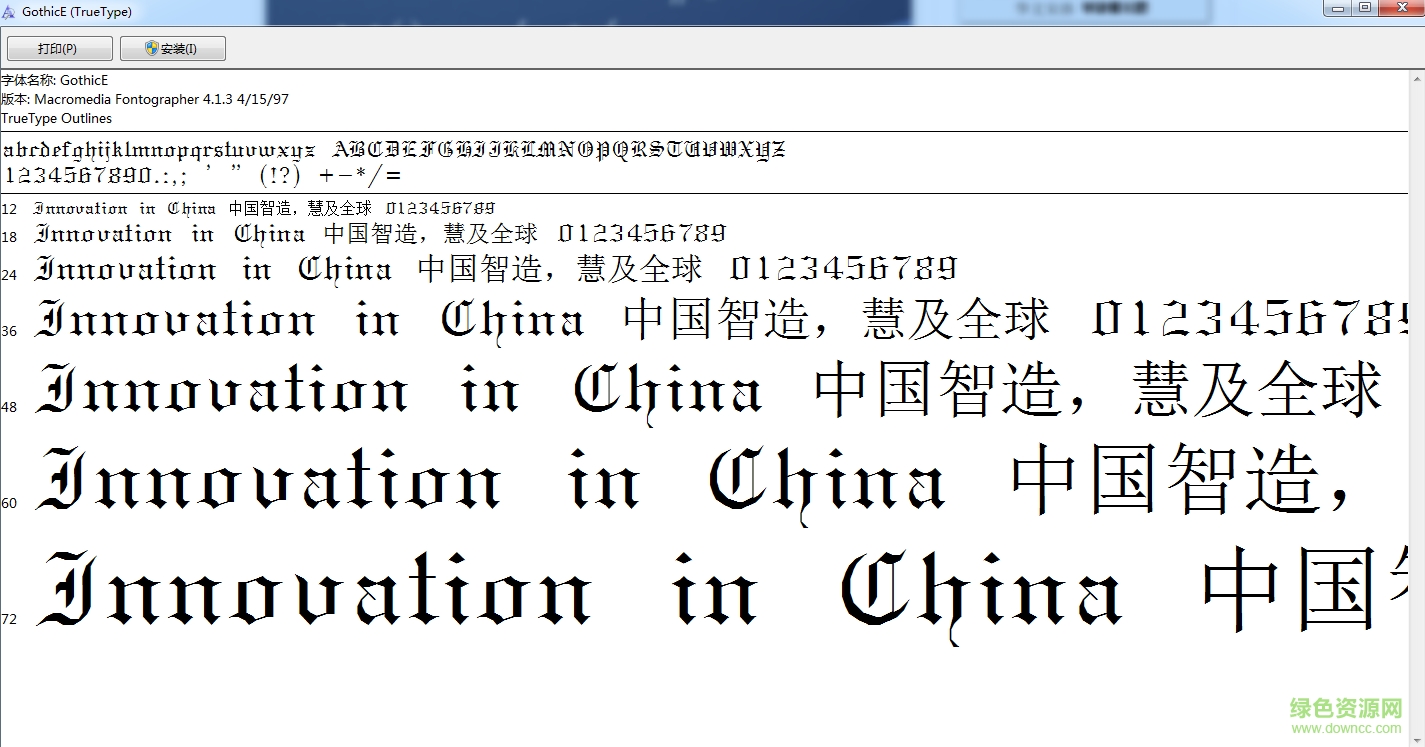
gothice字體是一款復(fù)古風(fēng)格的哥特式字體,線條繁復(fù),花紋華麗,另類又獨(dú)特,非常抓人眼球,該字體常用于裝飾方面,需要的朋友快來綠色資源網(wǎng)下載吧!
你可以用很多形容詞來描述它們:經(jīng)典、藝術(shù)、怪誕、神秘甚至臟兮兮!但這些都抵擋不住它給你的作品蒙上一層黑暗復(fù)古的魅力!